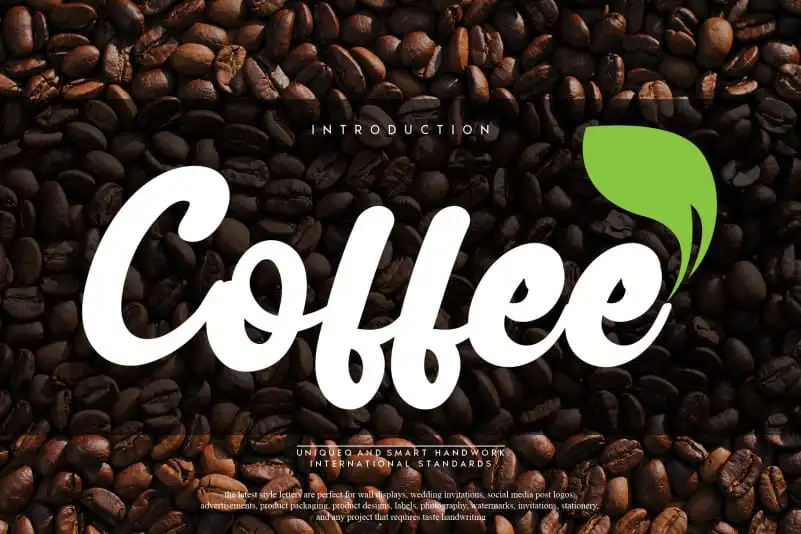
Coffee Script Font – Download Grátis
Esta página de download apresenta a Coffee Script Font, uma cunha especial para quem valoriza criatividade e experiências únicas no design. Introduzida pelo designer andikastudio nesta categoria de fontes manuscritas, Coffee Script oferece um toque autêntico e pessoal aos seus projetos digitais. Com seu estilo elegante e personalizado, esta fonte não apenas ajuda a destacar o texto de maneira única, mas também adiciona um toque único que torna cada obra de arte diferente. Se você está buscando uma fonte para dar vida à sua ideia criativa, Coffee Script é uma excelente escolha.